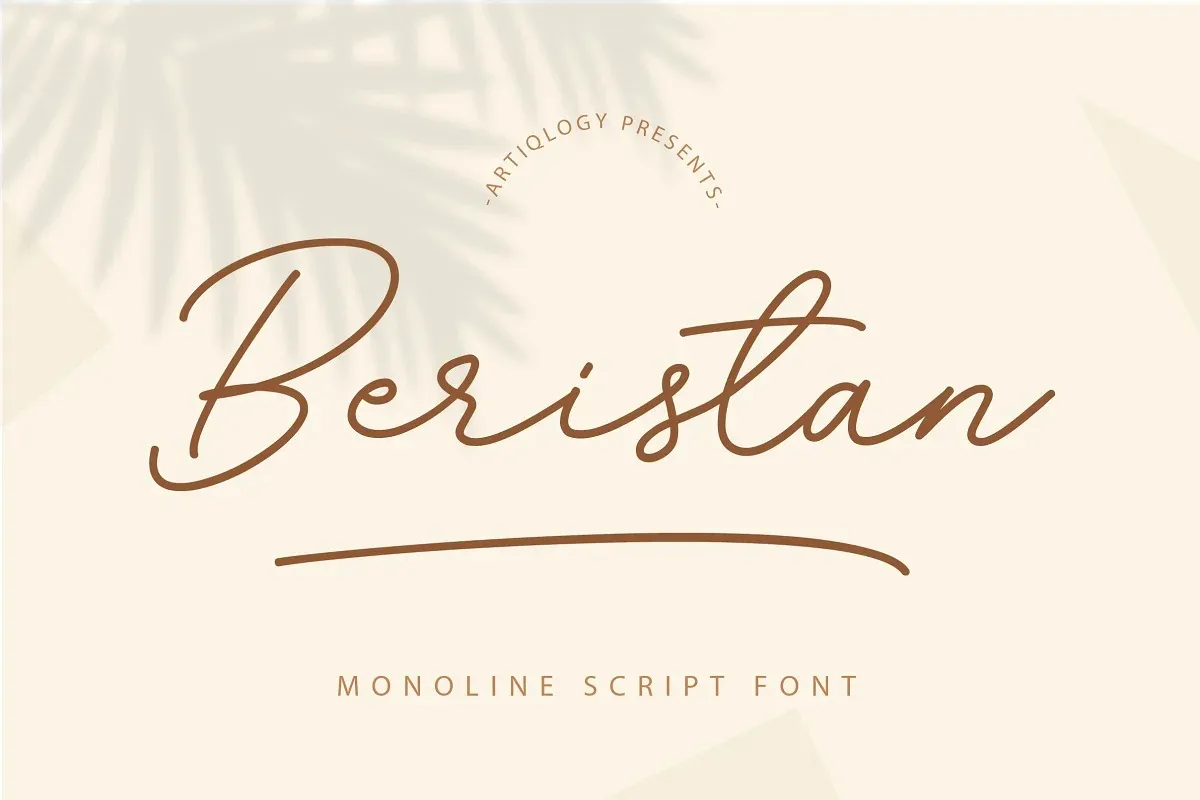
Beristan Font
A Beristan Font é uma elegante tipografia escrita à mão que oferece um estilo moderno e sutilmente sábio para criar projetos de design incrivelmente belos. Seus traços delicados têm a capacidade única de agregar um toque romântico ao seu trabalho, tornando-a perfeita para projetos como convites de casamento, arte em cartão de visita e postagens de redes sociais chamativas. Suas linhas fluidas são uma ótima escolha para aqueles que buscam um equilíbrio entre a modernidade e o encanto tradicional. A Beristan Font é ideal para criar mensagens pessoais, ou mesmo artigos profissionais com um toque delicado que deixará sua obra de arte ainda mais inovadora e especial. Inspirada no estilo romântico e contemporâneo, essa fonte é uma excelente adição aos seu portfólio. Aproveite-a para criar designs inspiradores que capturam a essência da moda atual, ao mesmo tempo em que mantêm um toque de charme e sofisticação com sua delicada escrita à mão.